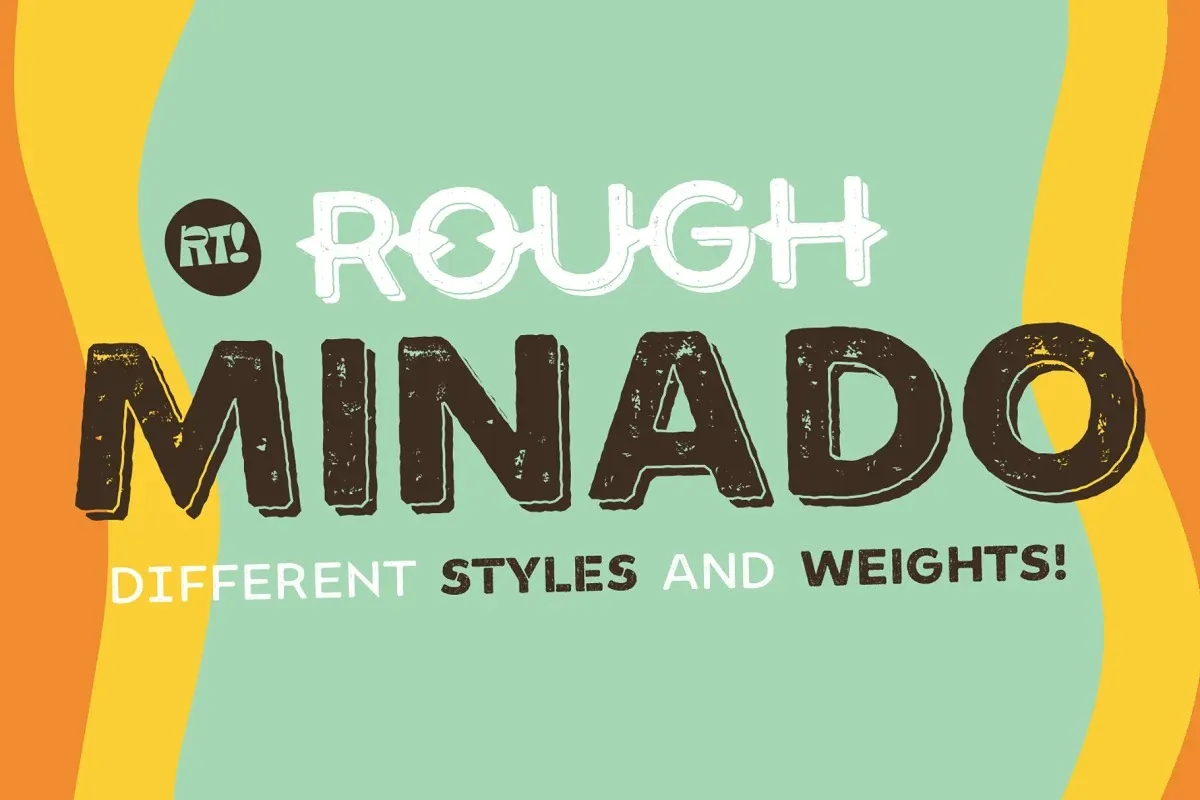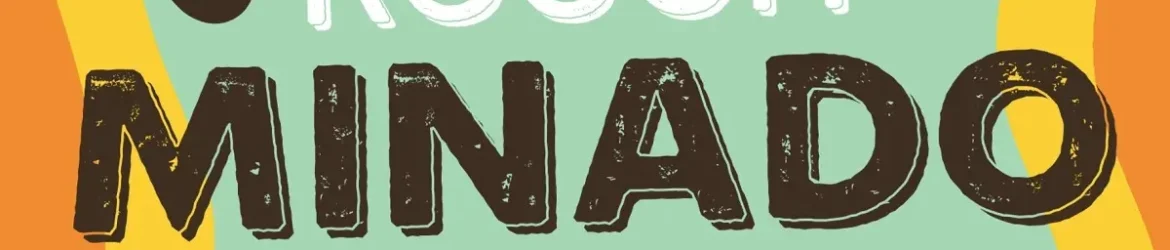
A Minado Rough Font é uma elegante mistura entre fontes romanas manuais e serifas, mantendo a simplicidade e modernidade de suas irmãs serifas semicírculares. Essa fonte única, criada por Rodrigo Typo através da 99designs, oferece uma variedade de seisteen estilos que vão além da simples elegância: pode ser usada para dar um toque profissional ou para criar uma atmosfera nostálgica e vintage em seu design. Cada caracter é meticulosamente traçado à mão no papel, criando uma sensação natural na forma do caractere. O efeito texturizado de rusticidade dá ao design um estilo retrô e vintage encantador. Esta fonte perfeita para aqueles que buscam um equilíbrio entre simplicidade sofisticada e arquejo nostálgico, sem comprometer o resultado final.